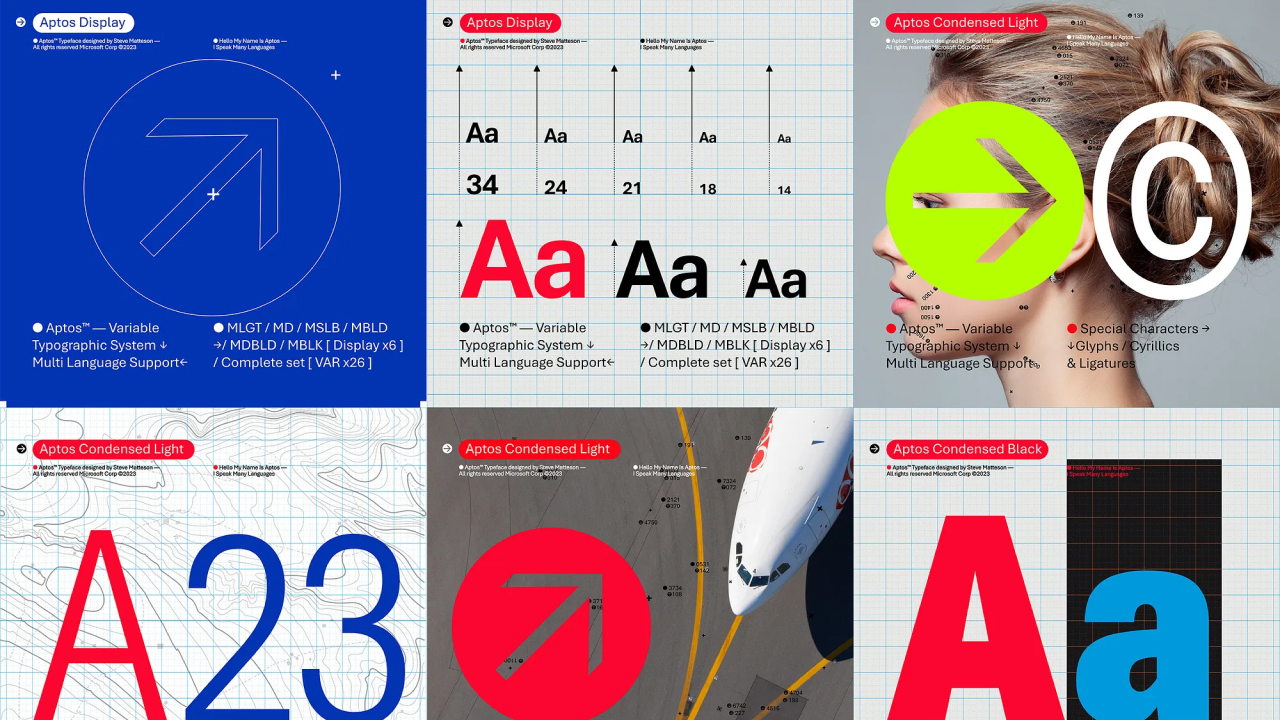
Microsoft сменит основной шрифт Calibri на Aptos
Компания решилась на очередные изменения спустя 15 лет
Microsoft впервые за 15 лет изменит установленный по умолчанию шрифт с Calibri на Aptos. Aptos легче читать, он больше подходит для экранов с более высоким разрешением. Об этом сообщил в блоге главный менеджер по дизайну программ Microsoft Office Си Дэниелс.
Новый шрифт не имеет засечек, в нём преобладают простые и ровные штрихи, поэтому он легко читается. «Aptos, состоит из различных геометрических форм, он смелый, чёткий и сдержанный. Он сочетает множество разных языков и тонов», — говорится в его описании.
Шрифт создан дизайнером Стивом Маттесоном, который ранее разработал шрифты TrueType и Segoe. Aptos получил название в честь города в Калифорнии.
Aptos по умолчанию установится в программах Office: Word, Outlook, PowerPoint и Excel. «Мы приступаем к заключительному этапу крупного обновления, в ходе которого Aptos будет отображаться в качестве основного шрифта по умолчанию для сотен миллионов пользователей», — отметил Дэниелс.
Напомним, что Calibri был шрифтом по умолчанию для продуктов Microsoft с 2007 года, до него основным был Times New Roman. В 2021 году Microsoft сообщила о желании заменить Calibri и заказала у дизайнеров разработку оригинальных пользовательских шрифтов: Bierstadt, Grandview, Seaford, Skeena или Tenorite. В итоге шрифт Bierstadt выиграл голосование пользователей, а затем сменил название Aptos. Остальные шрифты также будут доступны пользователям.